La tipografía facial de Beatrix Gevigney
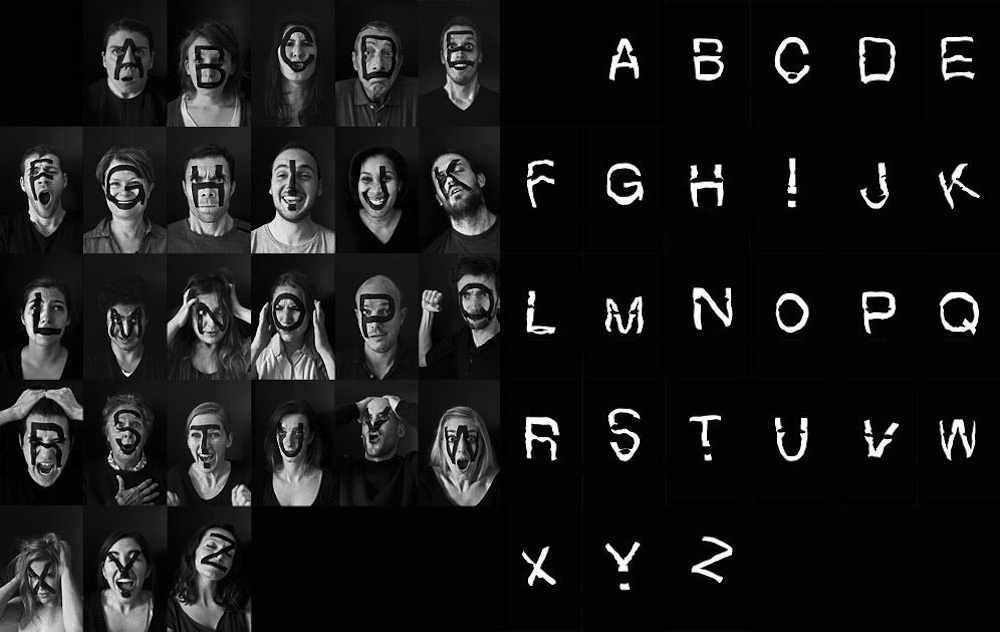
«La forma es la parte inferior que se eleva a la superficie». Lo dijo Víctor Hugo y la creativa francesa Beatrix Gevigney lo ha tomado como base para su nuevo proyecto tipográfico. Las letras que ella ha diseñado están inspiradas en emociones humanas verdaderas. Un abecedario como salido de dentro de los rostros que encontramos en Fubiz.
La D, según Gevigney, es de duda (dubitatif), y también son unas cejas encorvadas y unos labios volteando en sentido opuesto. La L es de lloroso (larmoyant), y requiere una boca fina y plana forzosamente cerrada, para darle su arista vertical a la letra. La R es de Rageur (enfado en francés), y los pliegues que brotan alrededor de una nariz enojada simbolizan perfectamente la parte inferior de ese símbolo alfabético. Las curvas de la S de sorpresa (surpris) giran en un rostro por sí mismas.
La autora, según describe en su presentación, tomó las esquinadas formas de la tipografía Helvetica como abono y comenzó a darle un sentido humano a ese abecedario digital.
Una persona tras otra, hasta 26, fue transformando las expresiones faciales de sus modelos en símbolos alfabéticos. Primero debía pintar meticulosamente los rostros para que no quedara ni una T sin sus vértices ni una O sin sus curvas. Lo siguiente era convencer a la personificación de su tipografía de adquirir el gesto que simbolizaba su dibujo. Por último, había que escoger la foto que hubiera cazado la letra perfecta dentro de la cara perfecta. De ahí brotaría la estructura del símbolo en sí. «Se llama Tipografía Humana (Human Type)», da por explicado el por qué Gevigney.
«Cada letra corresponde a un sentimiento», indica. «Cuando el sujeto cobra vida, la letra se pliega a la expresión de su rostro». Cuando le piden que defina las características de su nueva tipografía las medidas que ofrece son «emocional y humana».